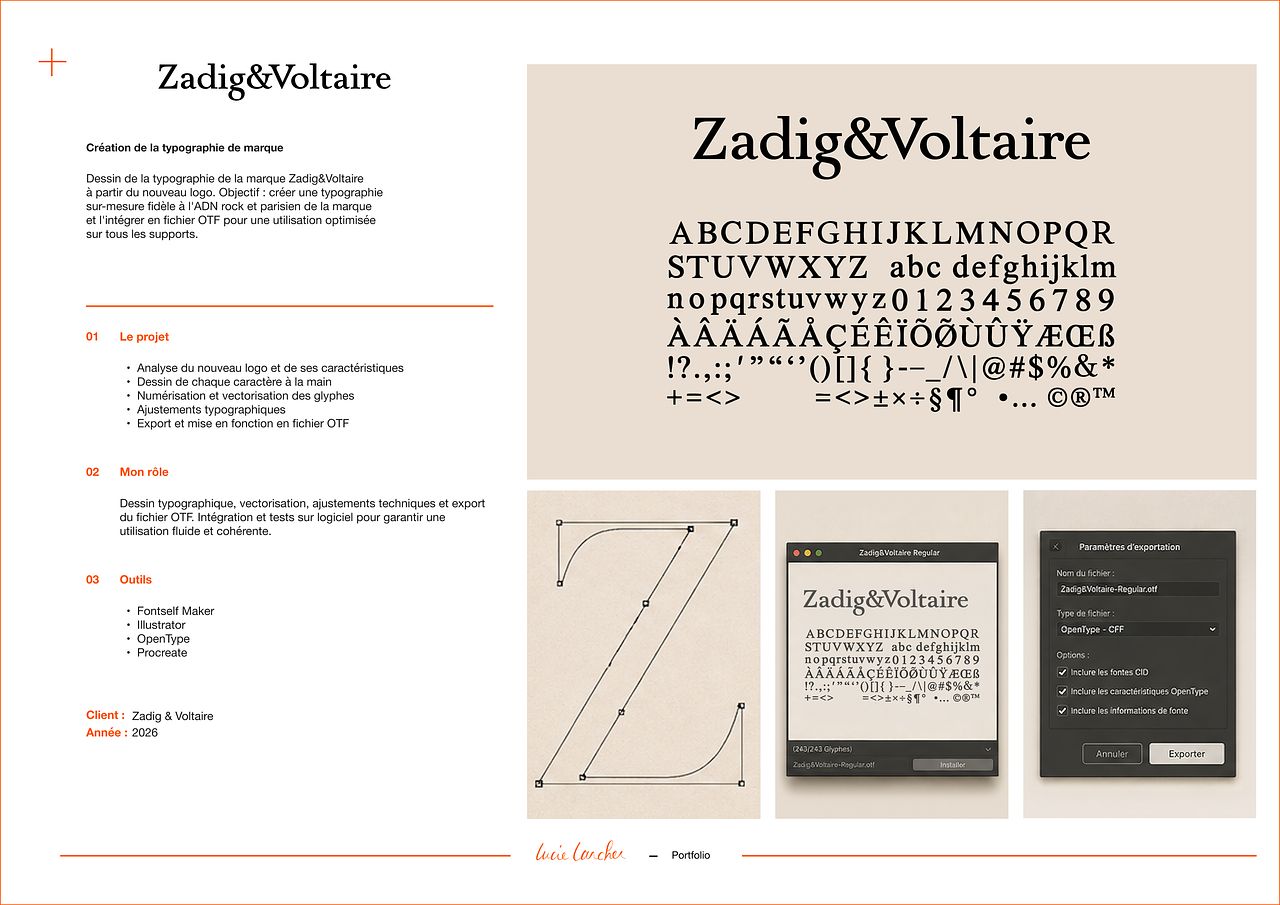
CRÉATION DE LA TYPOGRAPHIE DE MARQUE
Dessin de la typographie de la marque Zadig&Voltaire à partir du nouveau logo. Objectif : créer une typographie sur-mesure fidèle à l'ADN rock et parisien de la marque et l'intégrer en fichier OTF pour une utilisation optimisée sur tous les supports.